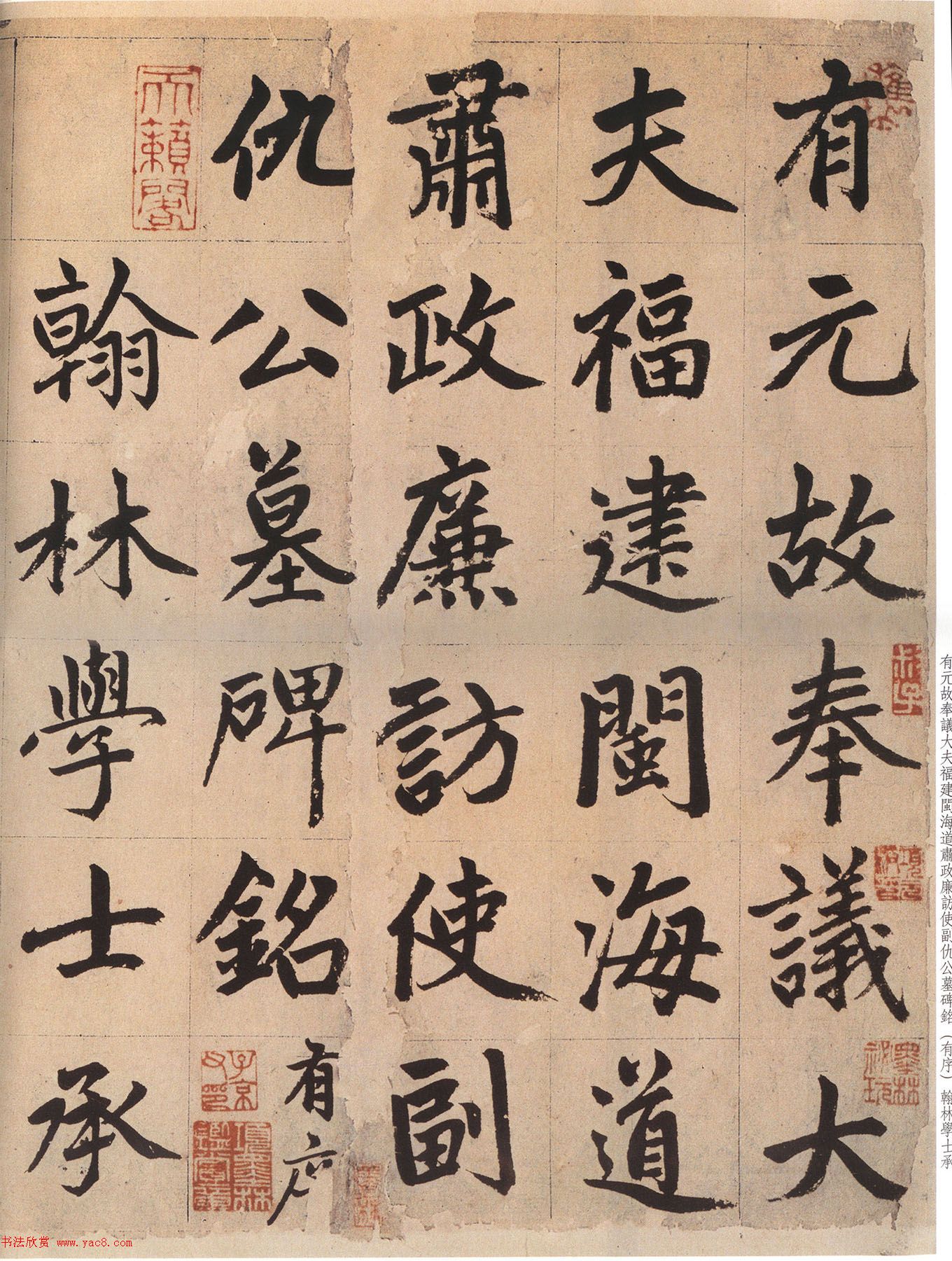
字体全名: 汉标赵孟頫仇君墓碑铭
字体简介: 下载须知:本字库非标准GB2312字库。本字库只包含了赵孟頫《仇君墓碑铭》真迹上的“1310个字”。详见图样。元代赵孟頫《仇君墓碑铭》,行楷书墨迹。篆题引首《有元故奉议大夫福建闵海道肃政廉访副使仇府君墓碑铭》二十四字, 其中“建闵海道肃政廉访”八字原已损缺,系后人为之补书。《仇锷墓碑铭》于延祐六年(1320)书,是其晚年力作。运笔方整有力, 遒丽老健,一笔不苟,骨气深稳,与常见赵书妩媚甜润不同。赵孟頫的书法以楷书和行书最好。此书是他楷书代表作之一,他的楷书用笔流畅随意,但又出规入矩,法度森严,其结体疏朗俊秀,飘逸洒脱,几乎无瑕疵可言。